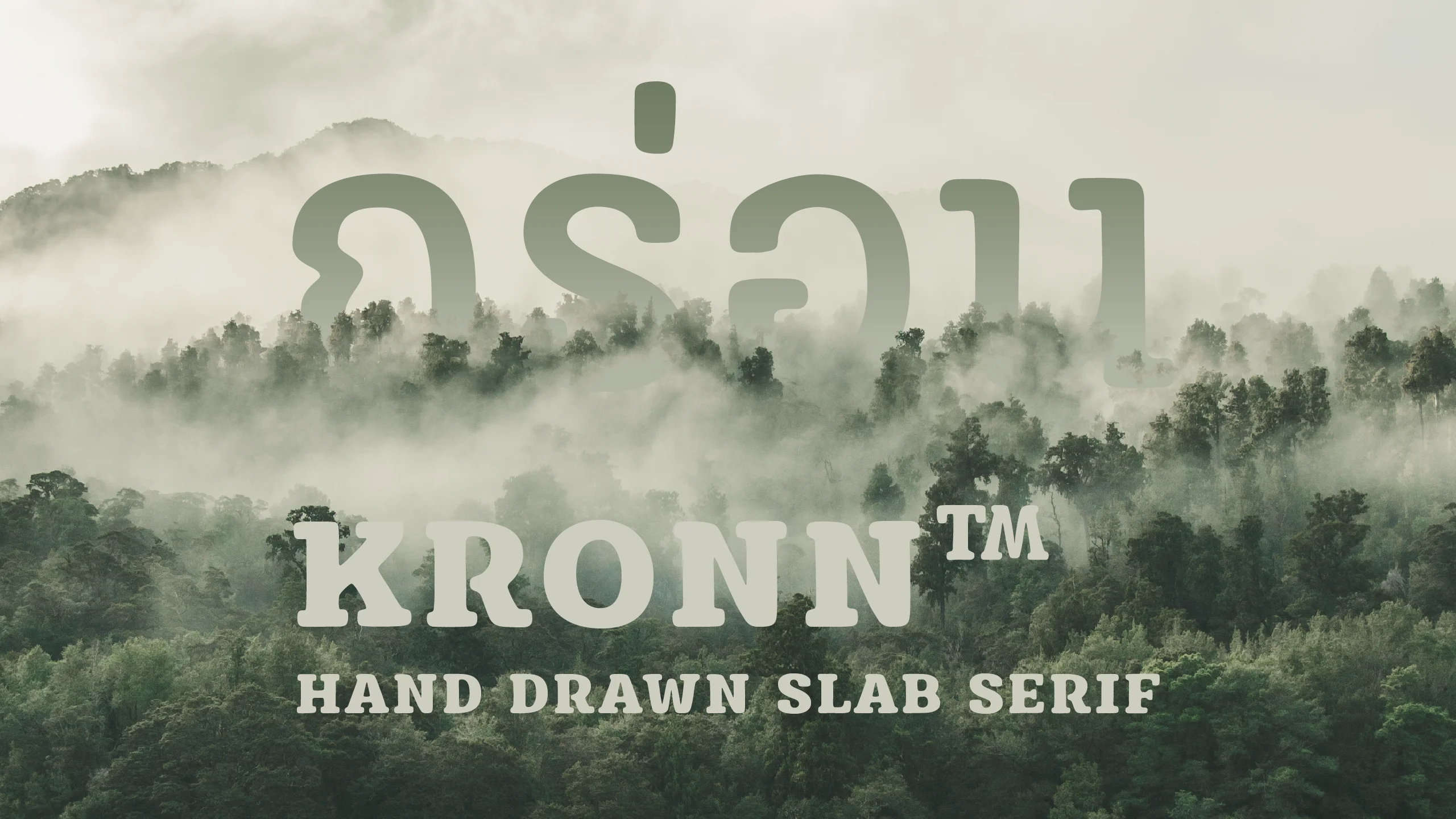
ส่วนผสมที่ลงตัวระหว่างความนุ่มนวลและความบึกบึน รังสรรค์ขึ้นเพื่อเป็นชุดอักษรพาดหัวที่มีตัวตนชัดเจนที่สุดชุดหนึ่ง โดยมีจุดเริ่มต้นจากการร่างแบบด้วยการเขียนมือ (Hand-drawn) ทำให้ทุกลายเส้นมีเสน่ห์ของความไม่หยุดนิ่ง แฝงไปด้วยความรู้สึกที่เป็นธรรมชาติและดูมีมิติที่แตกต่างจากฟอนต์ Geometric ทั่วไป มอบบุคลิกที่ดูเรียบง่ายแต่ทรงพลัง พร้อมที่จะสื่อสารข้อความของคุณออกไปได้อย่างหนักแน่นและน่าจดจำ ด้วยลักษณะของตัวอักษรที่มีความหนาเป็นพิเศษและมีรายละเอียดของความละมุนที่ซ่อนอยู่ "กร่อน | KRONN" จึงทำหน้าที่เป็นฟอนต์พาดหัว (Display Font) ที่ช่วยสร้างความโดดเด่นให้กับงานออกแบบได้อย่างดีเยี่ยม ไม่ว่าจะเป็นงานสร้างแบรนด์ที่ต้องการภาพลักษณ์ที่ดูเข้าถึงง่ายแต่มีความมั่นคง หรืองานกราฟิกที่ต้องการกลิ่นอายของความเป็นงานคราฟต์ที่ทันสมัย ฟอนต์ชุดนี้จะช่วยเพิ่มน้ำหนักให้กับทุกการสื่อสารของคุณให้ดูน่าสนใจและเปี่ยมไปด้วยสไตล์ที่ไม่มีใครเหมือน